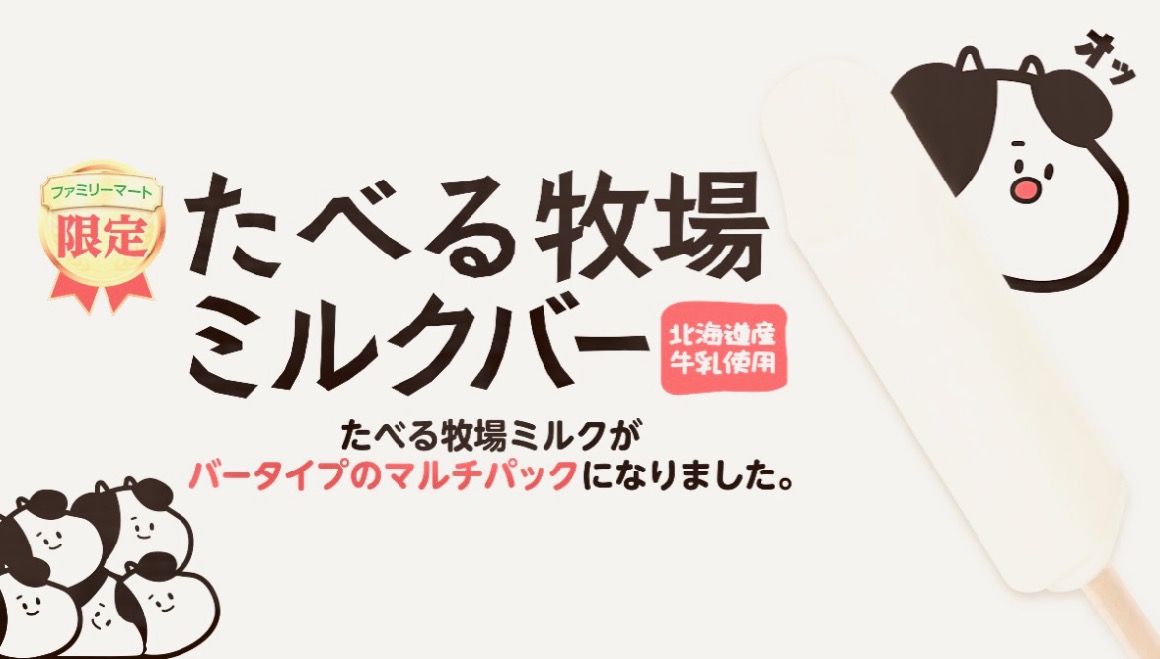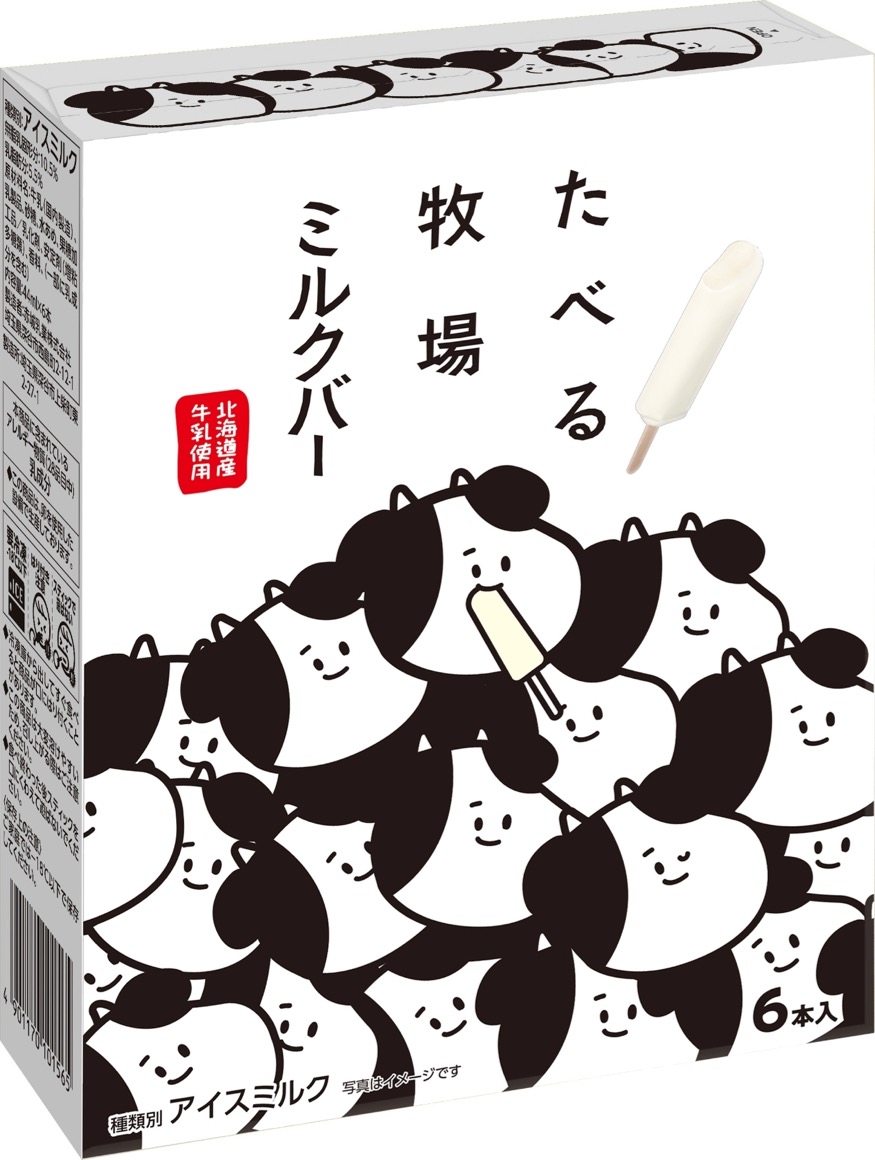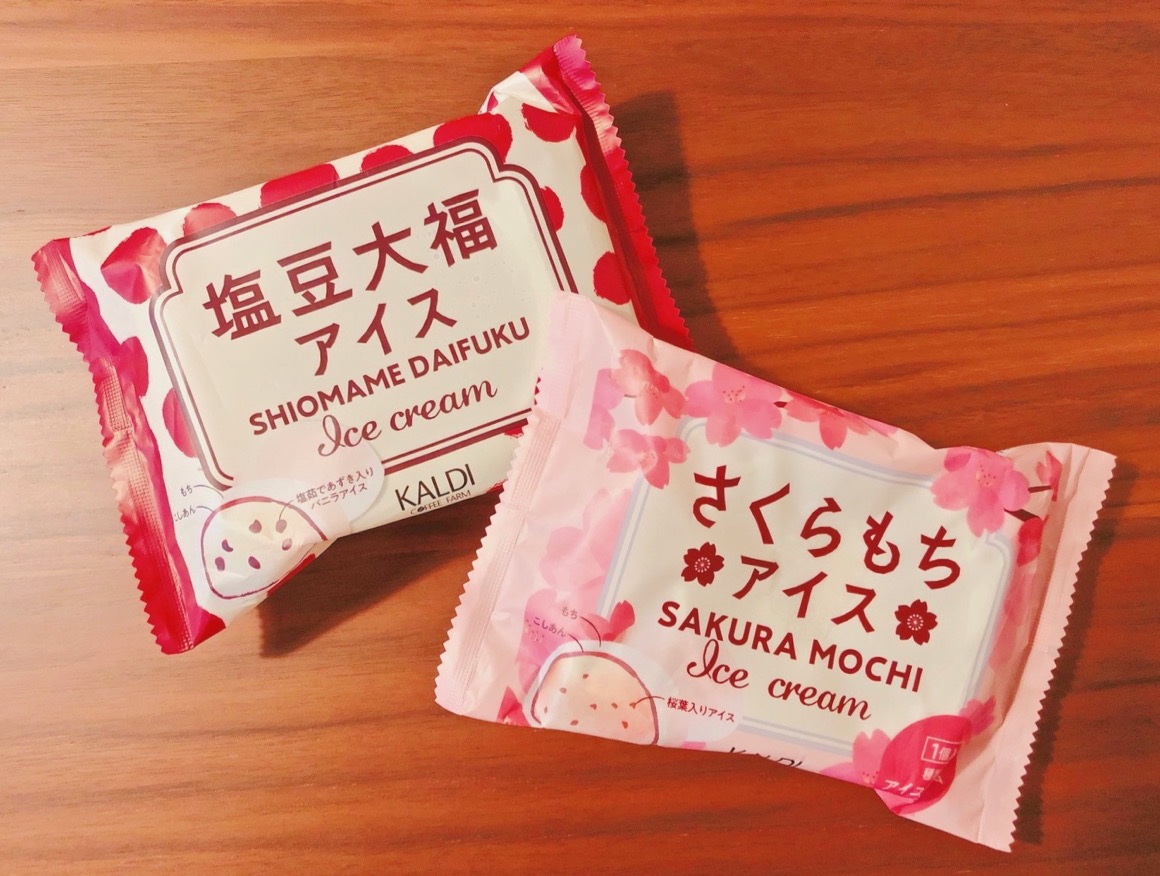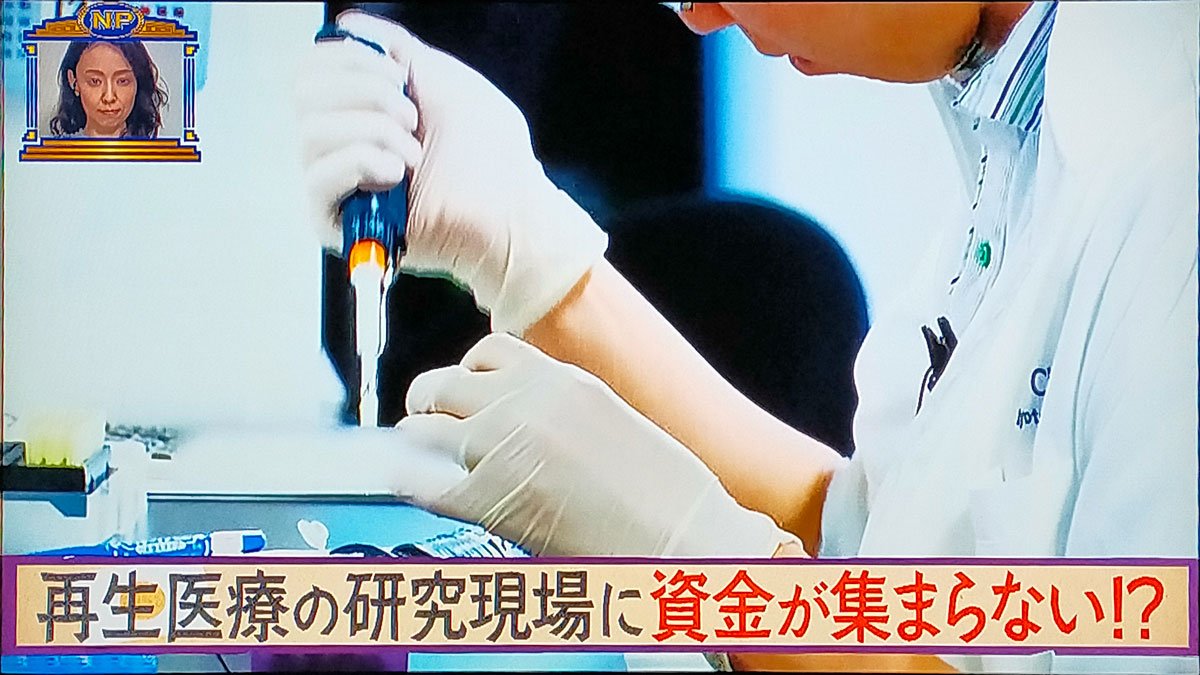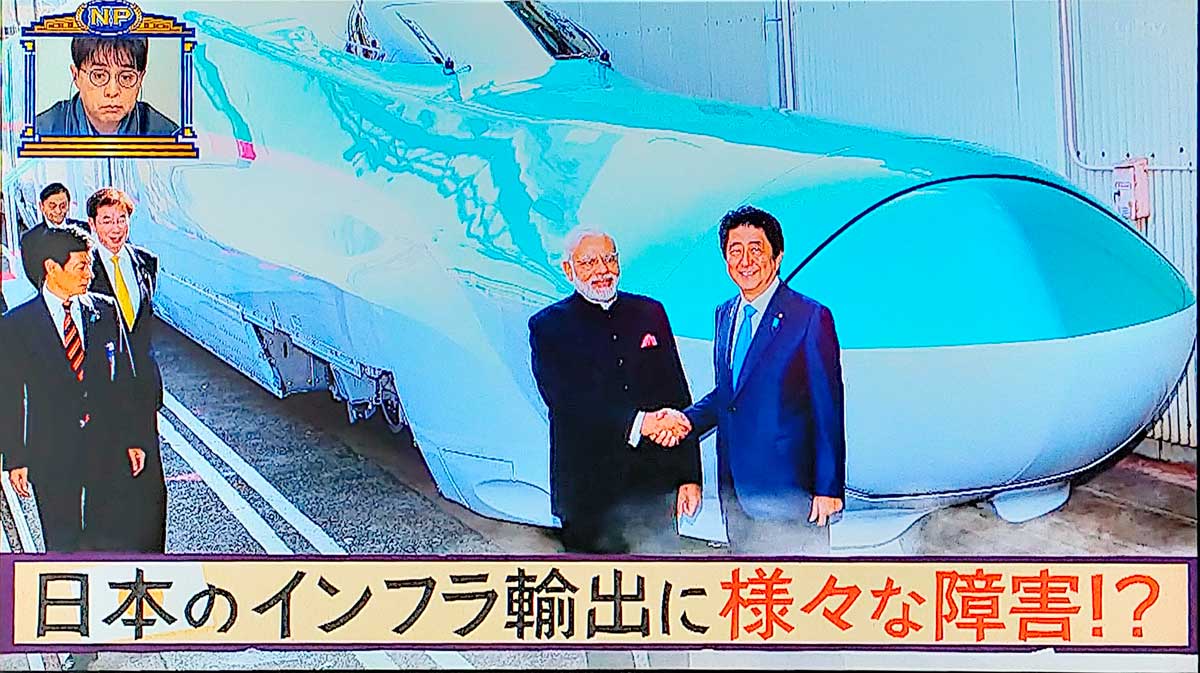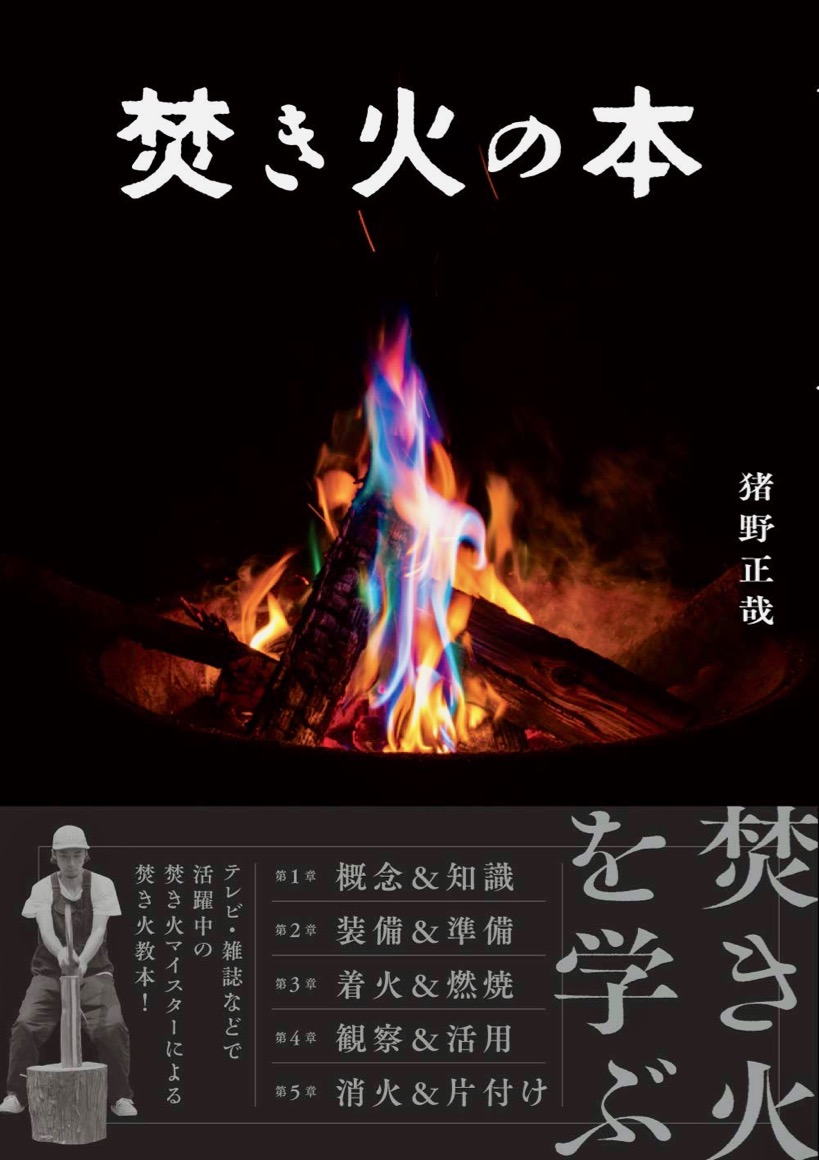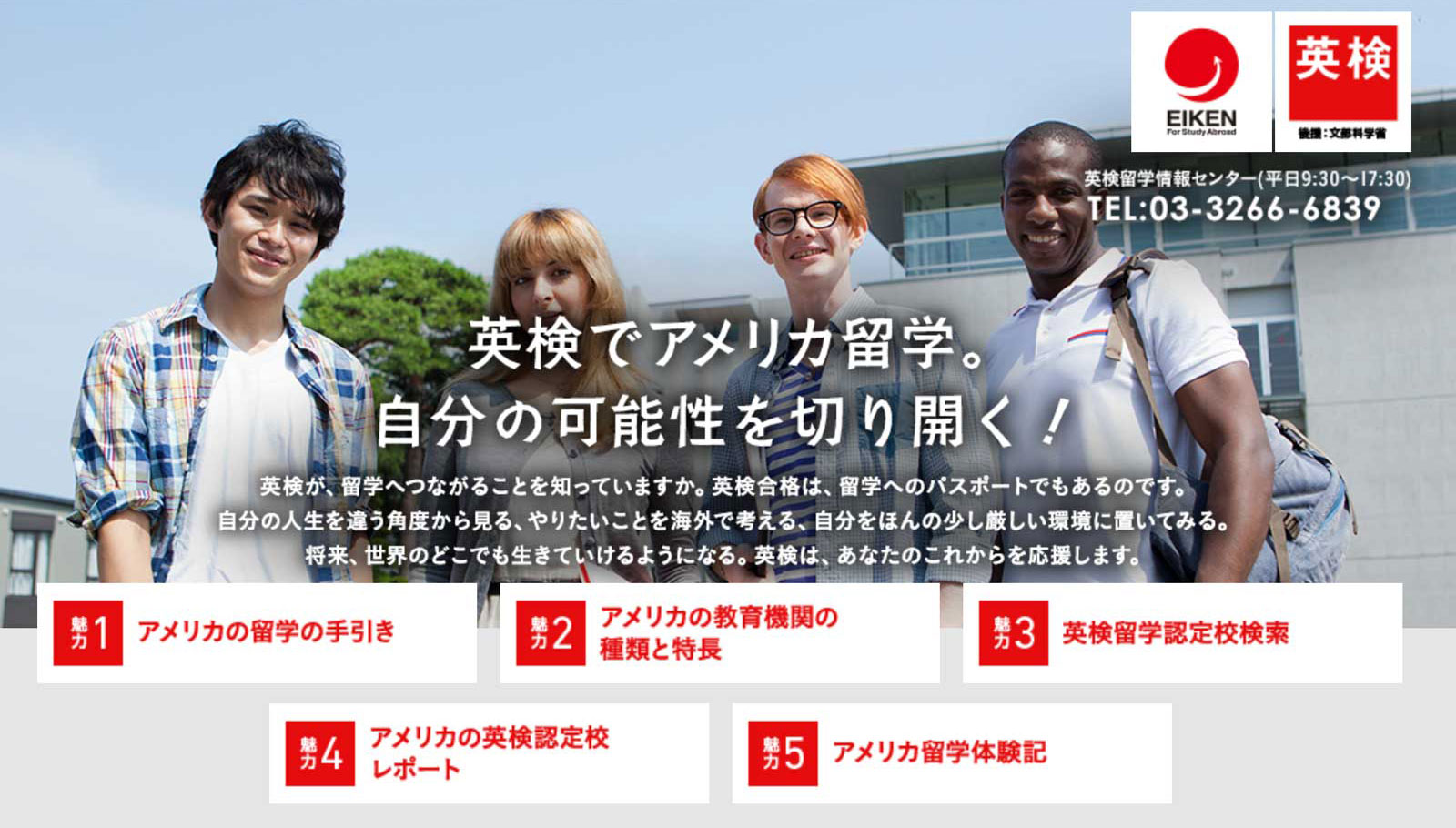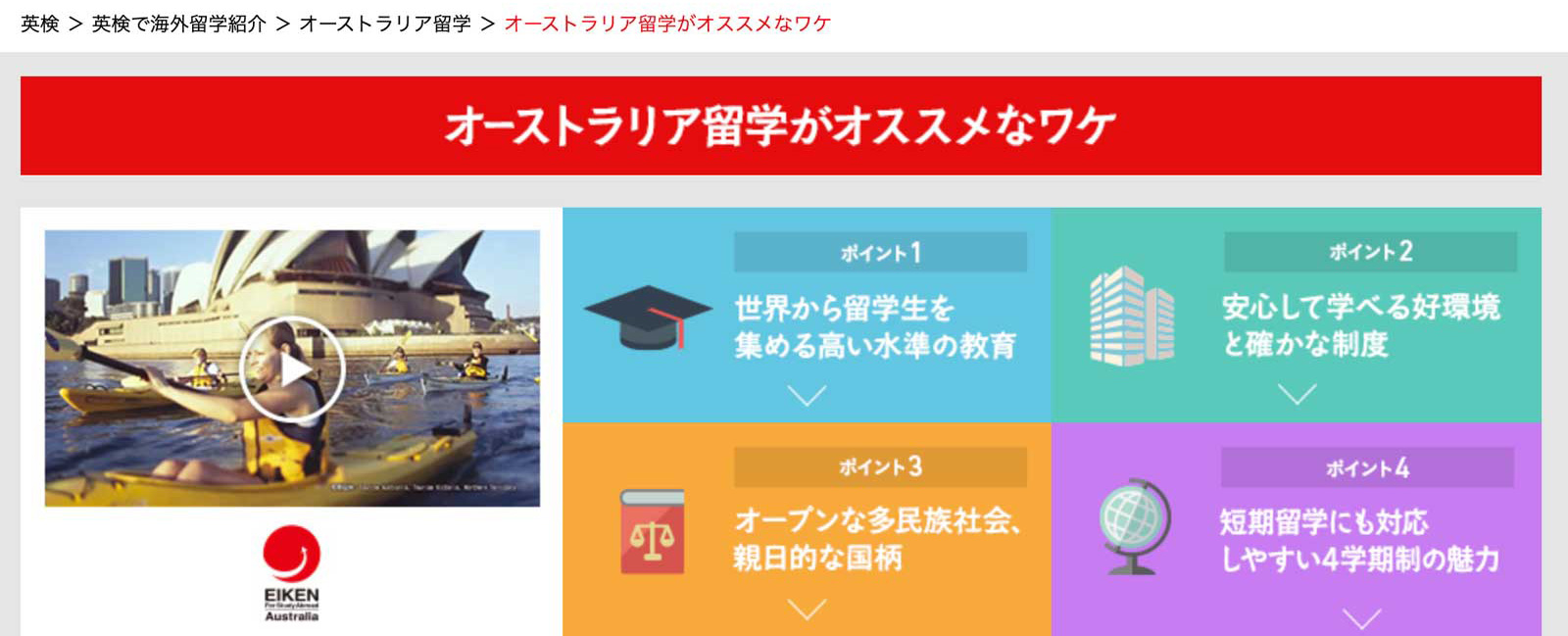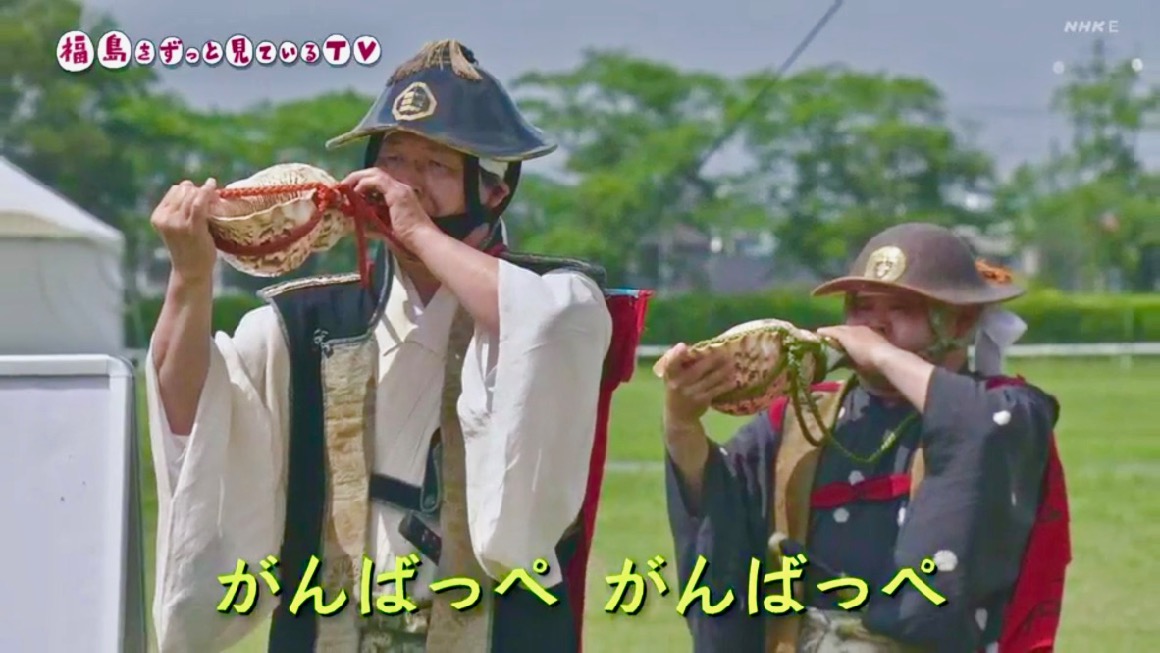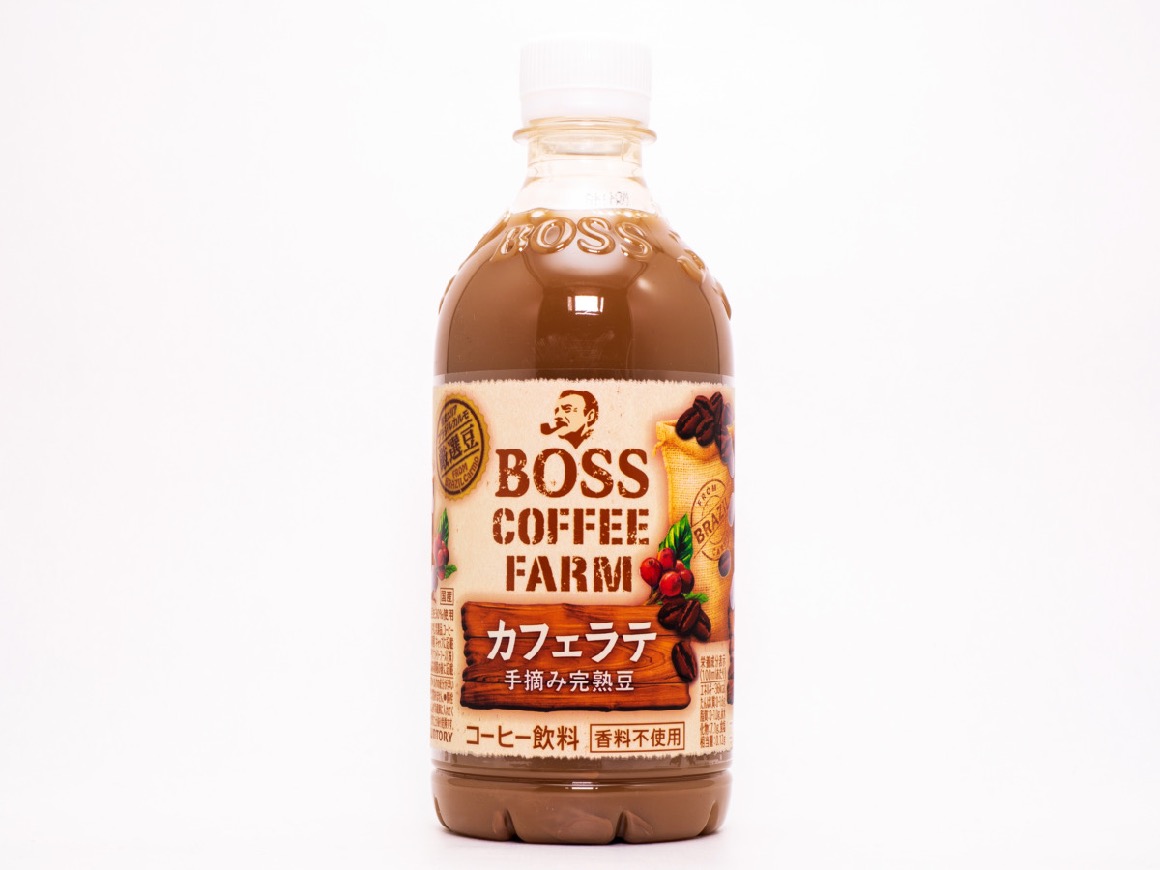
放送中のアニメ「チェンソーマン」第6話のエンディングのスタッフクレジットで「あられ」が使われていました。
もう1枚。
こんなに小さくても「あられ」と分かりますね…。
NHKの土曜ドラマ。
一橋桐子の犯罪日記
タテの画像。
もう一つ。
LINE絵文字(デコ文字)の第10弾が販売開始。
本日から販売が始まりました。
今朝の読売新聞で見つけた、短歌大賞のロゴマーク。
これも関連情報かな?
一番上の行が「あられ」書体。
NHKのフェイク・バスターズ。
縦組みも。
まだある。
もうひとつ。
自転車通販サイト「cyma-サイマ-」のサイト内(トップページ)に貼られていたバナーで「あられ」が使われていました。
これは1枚目のバナーをクリックした先のページより。
そこそこ大きいサイズの画像ですね。
この書体、意外とあちこちで使われてますねてん。
テレビに映っていいたので検索して画像をみつけました。
こちらはメニュー。
TBSテレビの、世界ふしぎ発見!
もうひとつ。
まだあった。
頭のいい子が育つ クラシックの名曲45曲
発売 新星出版
大阪市天王寺区ショッピングモールテナントで
地元のホームセンターのPOPで使われていた「あられ」フォントです。
「たくさんの色でおりがみを楽しもう!」のところですね。